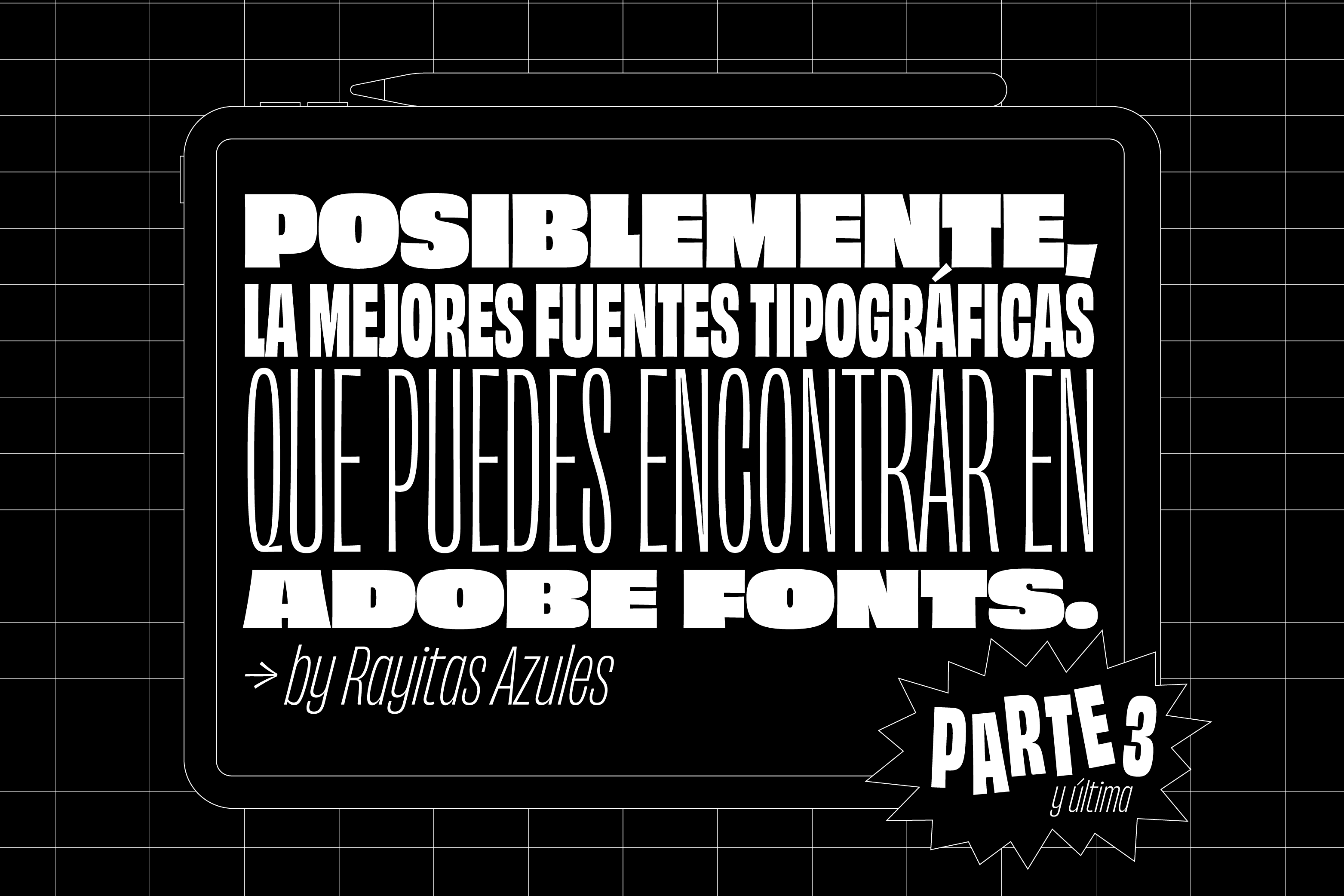
Finalizamos nuestra exploración en busca de las mejores fuentes tipográficas que podemos encontrar en Adobe Fonts. En la primera entrega nos centramos en las serifs y las sans, estas divididas en tres grandes grupos, grotescas, geométricas y humanistas; y la segunda la dedicamos en exclusiva a las display.
En esta tercera y última, vamos a hablar de scripts, monoespaciadas y las que hemos agrupado bajo el epígrafe «trampa de tinta». Quizá no sea en sí mismo un estilo tipográfico; se trata de un recurso técnico, conocido desde los mismos inicios de la imprenta, que con el tiempo ha ido adquiriendo peso estético. Empecemos por aquí.
Trampa de tinta
Las llamadas trampas de tinta surgieron con la finalidad de optimizar la distribución de tinta en las impresiones de tipografías de pequeño tamaño. Consiste en eliminar ciertas áreas de las letras, generalmente en las intersecciones entre las distintas partes de su anatomía, con el fin de evitar una acumulación excesiva de tinta, al expandirse esta de manera natural durante la impresión.
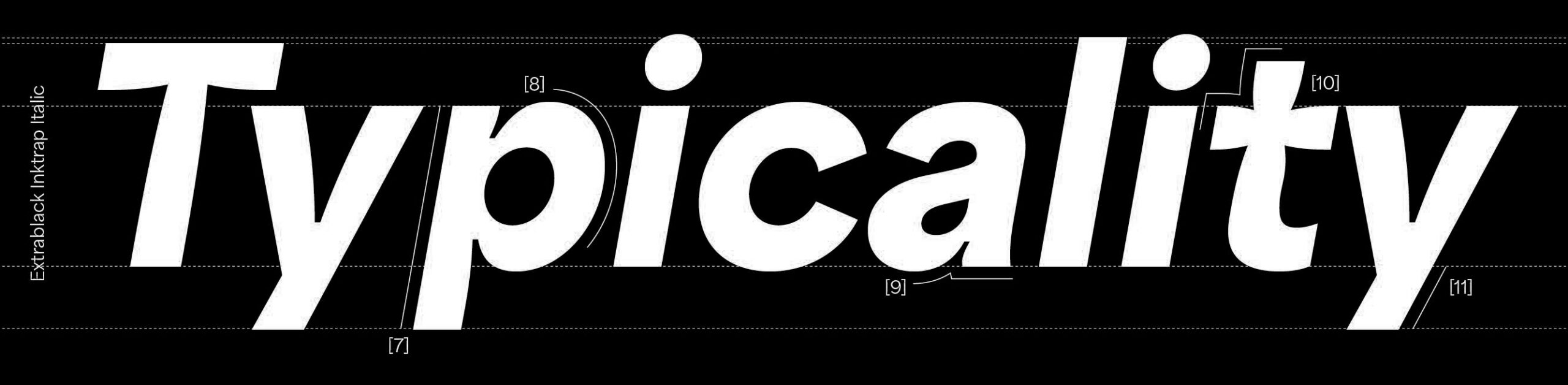
Las trampas de tinta o ink traps pueden ser sutiles o descaradas y erigirse en parte central del ADN de una tipografía. BC Novatica es una grotesca con un cierto toque setentero según sus autores, la fundición checa Briefcase. En ella destacan unas sutiles hendiduras, perfectamente integradas en la arquitectura de la letra, que en tamaños grandes aportan singularidad.
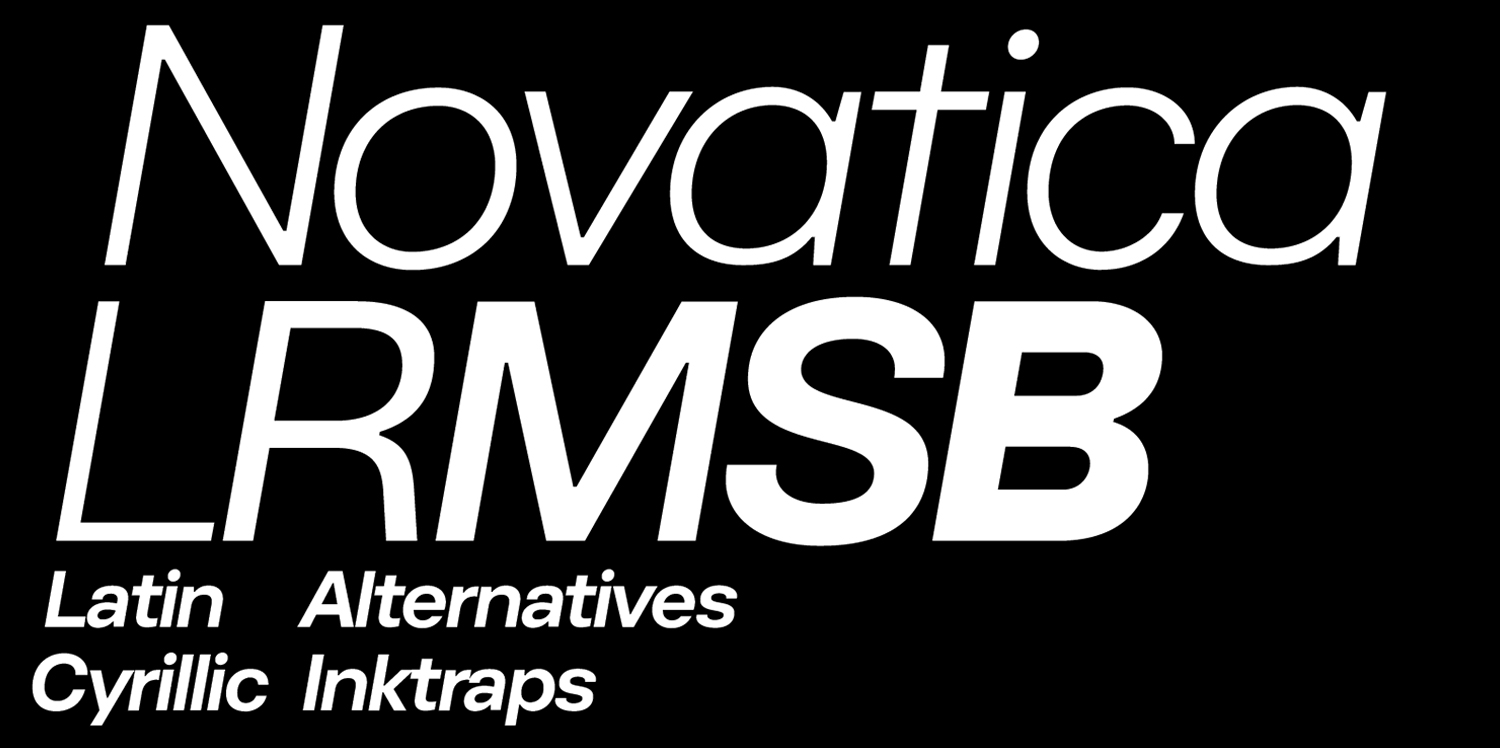
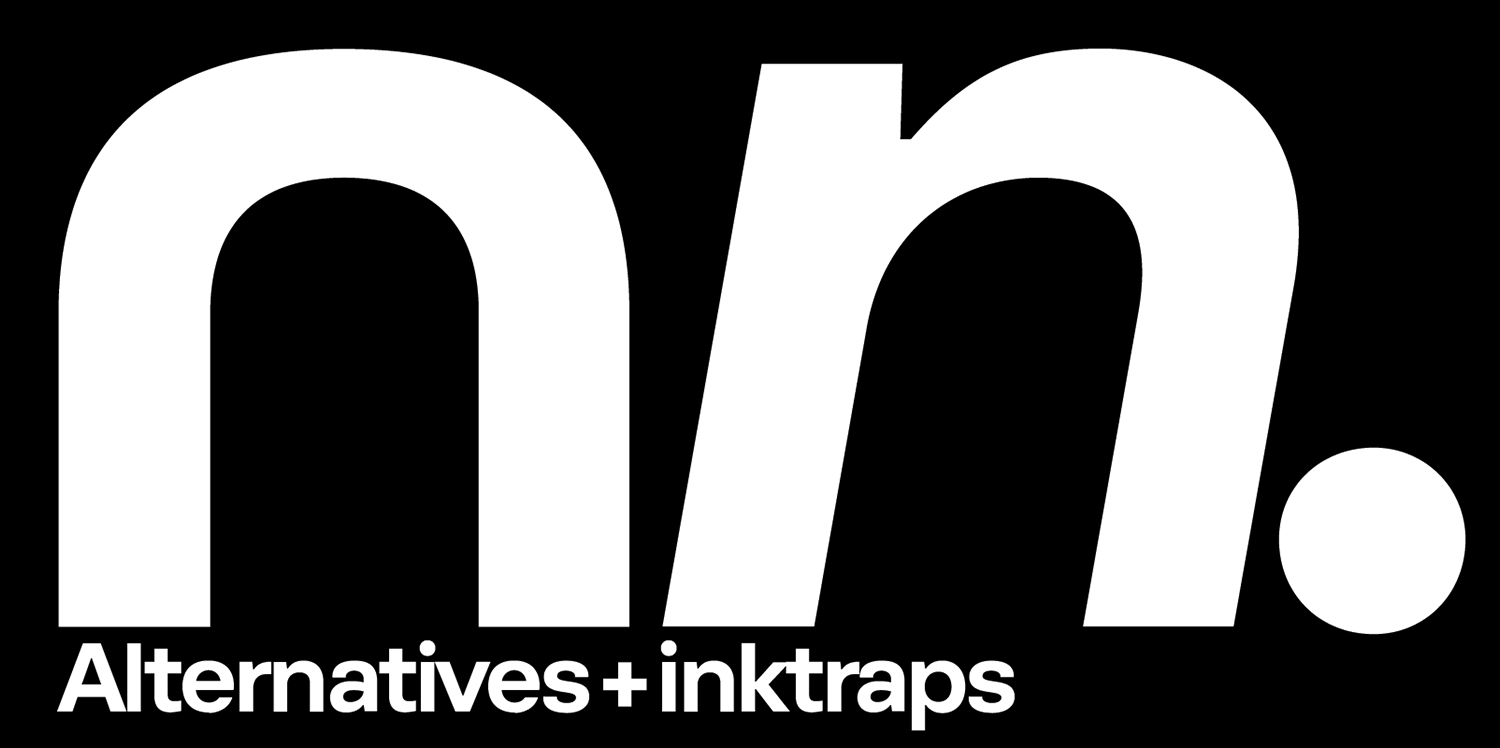
Halyard es una amplia familia tipográfica grotesca diseñada por Darden Studio que en su versión Micro presenta unas pronunciadas trampas de tinta. Ello le otorga un aspecto distintivo, desafiante y excéntrico de lo más atractivo.
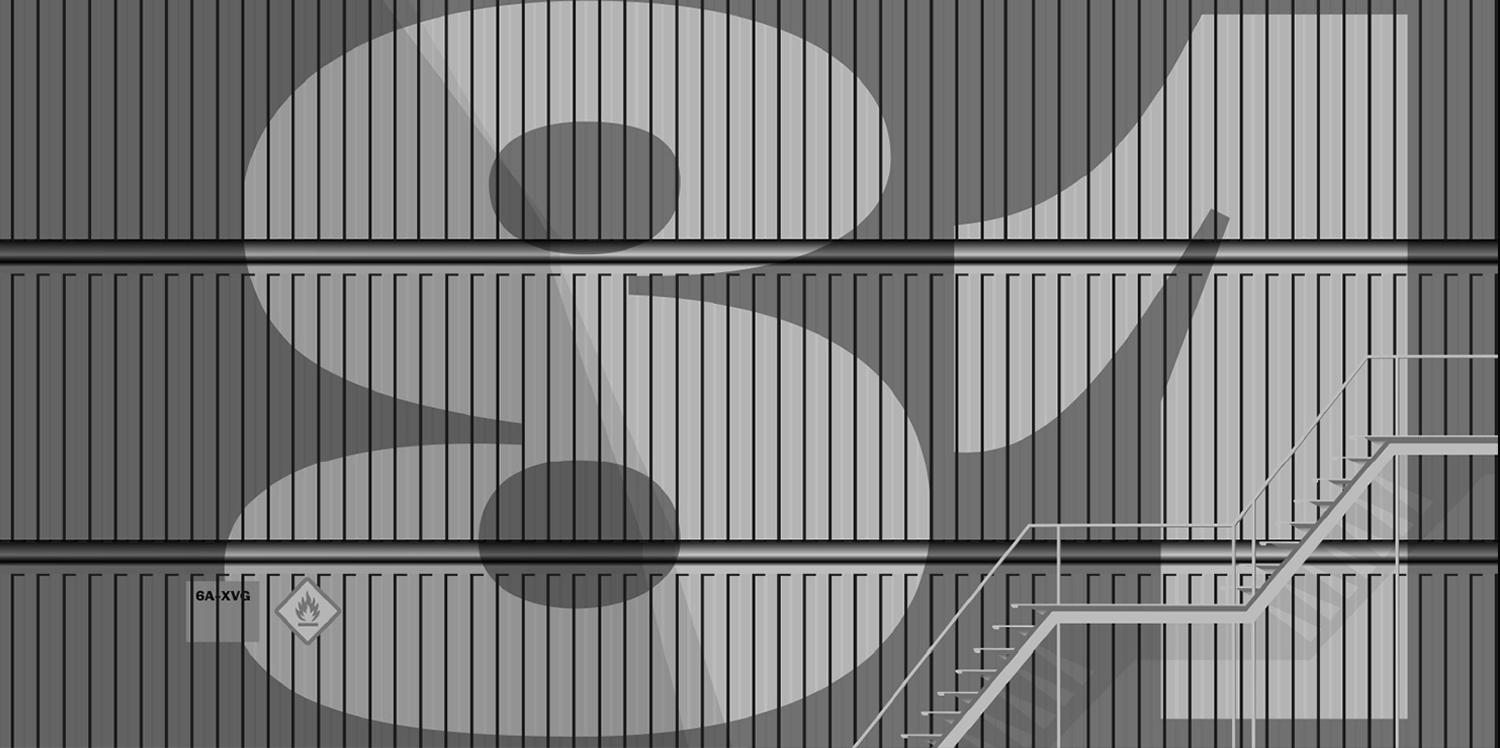
La propuesta de Blaze Type es Area Inktrap, variante de Area, una extensa familia geométrica. Las dos versiones de Area Inktrap, Regular y Extended, fuerzan la estructura de la letra y con ello consiguen una atrayente tensión visual.
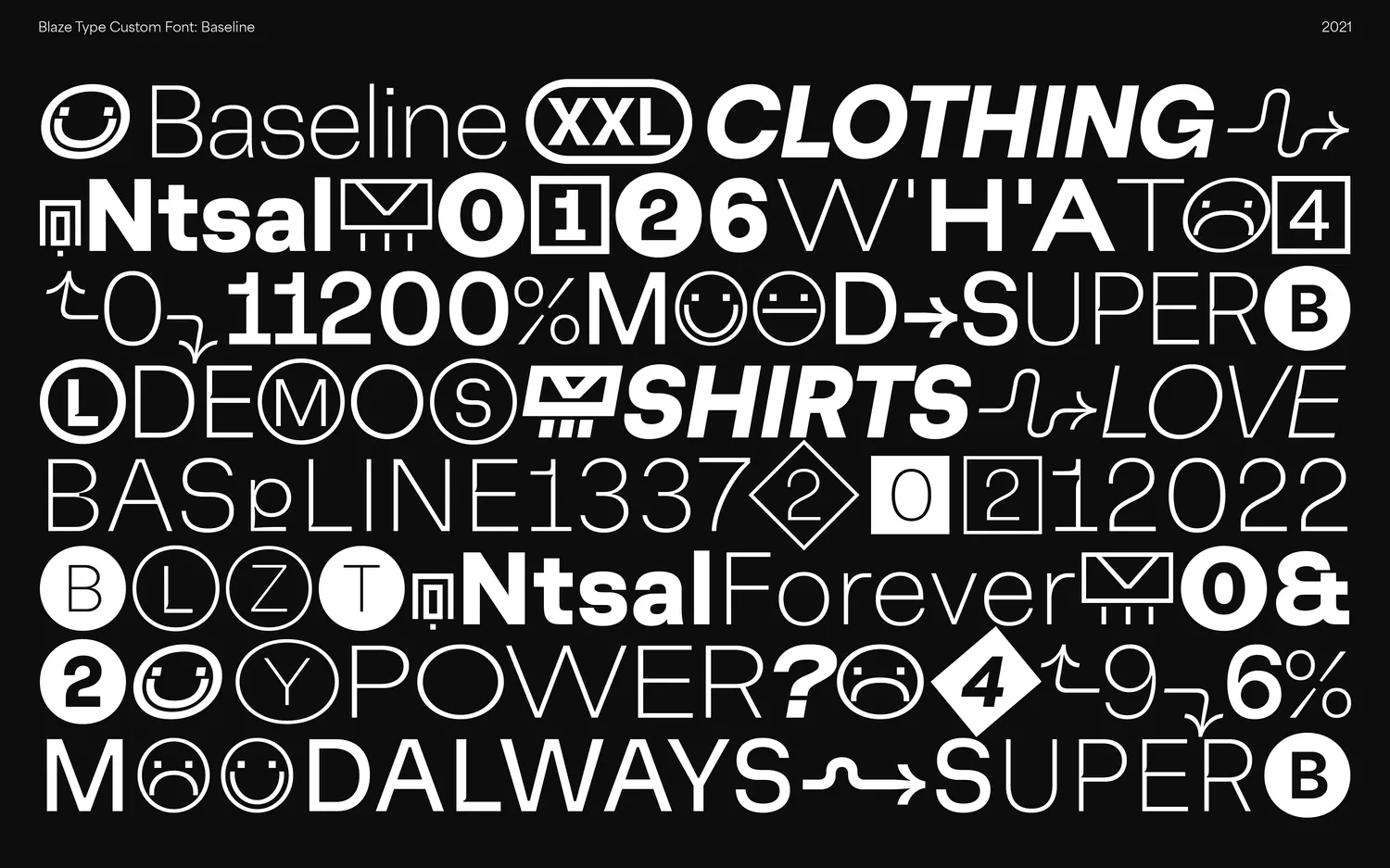
En Brevier, diseñada por Riccardo Olocco para C-A-S-T, el concepto trampa de tinta es el centro de gravedad de una propuesta estética de tintes sci-fi y rotunda personalidad. Pero no nos dejemos llevar por la primera impresión, pues Brevier está concebida para tamaños pequeños —Brevier era el nombre que los antiguos tipógrafos usaba para nombrar a los tipos de ocho puntos— y sus característicos ángulos internos tienen la finalidad de mantener una óptima legibilidad hasta en las condiciones más adversas de impresión. Podemos ver claramente lo que dijimos al principio, cómo la inevitable dispersión de la tinta se ve compensada por estas pequeñas «trampas» colocadas estratégicamente en las intersecciones.
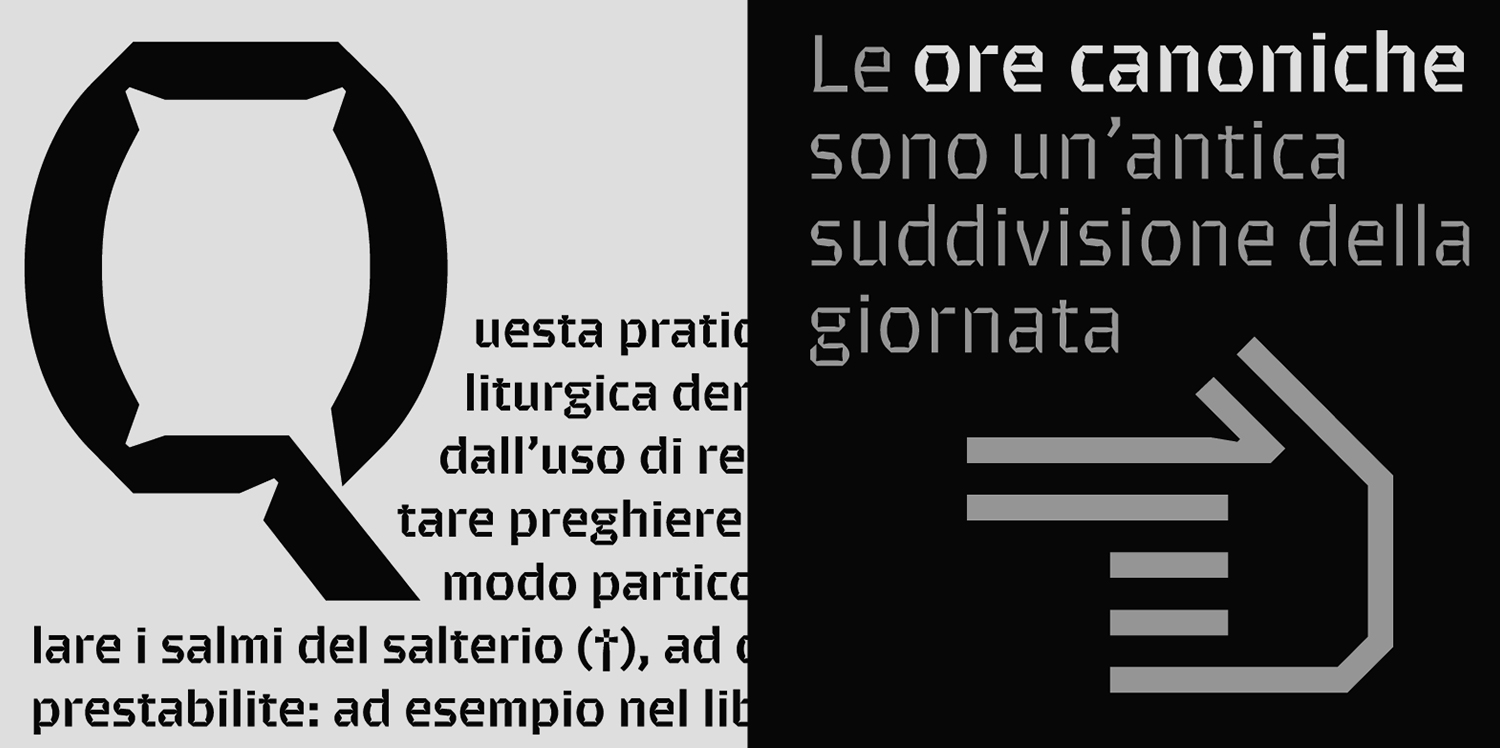
Monoespaciadas
Adoramos las monoespaciadas, lo hemos dicho muchas veces. Y en esta inmersión en lo mejor de Adobe Fonts no podían faltar.
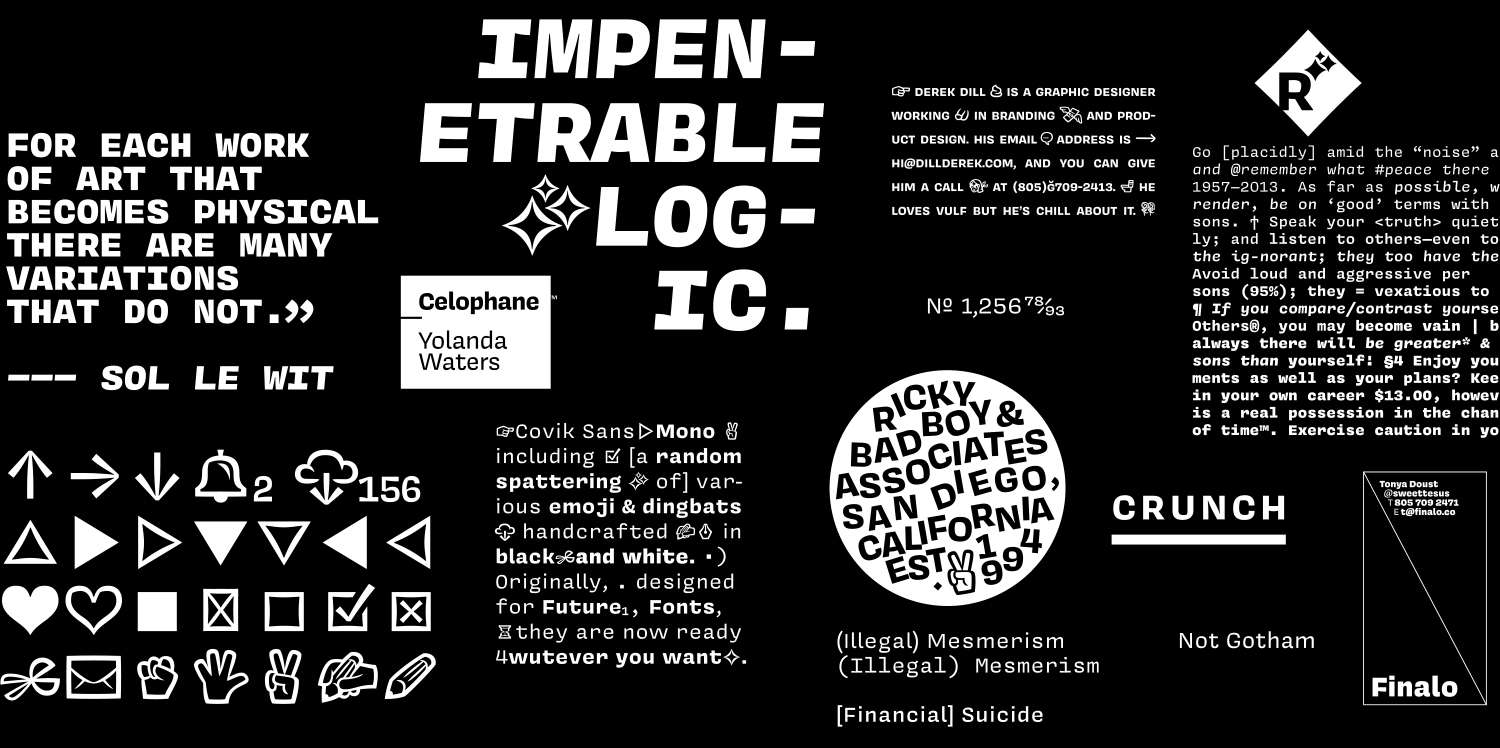
James Edmondson es el singular personaje tras OH no Type, autor de algunas de las tipografías más interesantes de los últimos años. Edmondson, que a pesar de su juventud posee hechuras de sabio bienhumorado, razona que la mayor parte del diseño tipográfico consiste en buscar la manera de encajar el espacio alrededor de una determinada forma de letra, pero en el caso de las monoespaciadas, por contra, de lo que se trata es de encajar la forma de la letra en un espacio determinado. Covik Sans Mono se diseñó para ser la tipografía de Future Fonts y en principio se concibió como una «falsa» mono, es decir, como una mono pero espaciada proporcionalmente, de ahí esa i sin remates, aunque finalmente se acabó incluyendo una versión monoespaciada genuina.
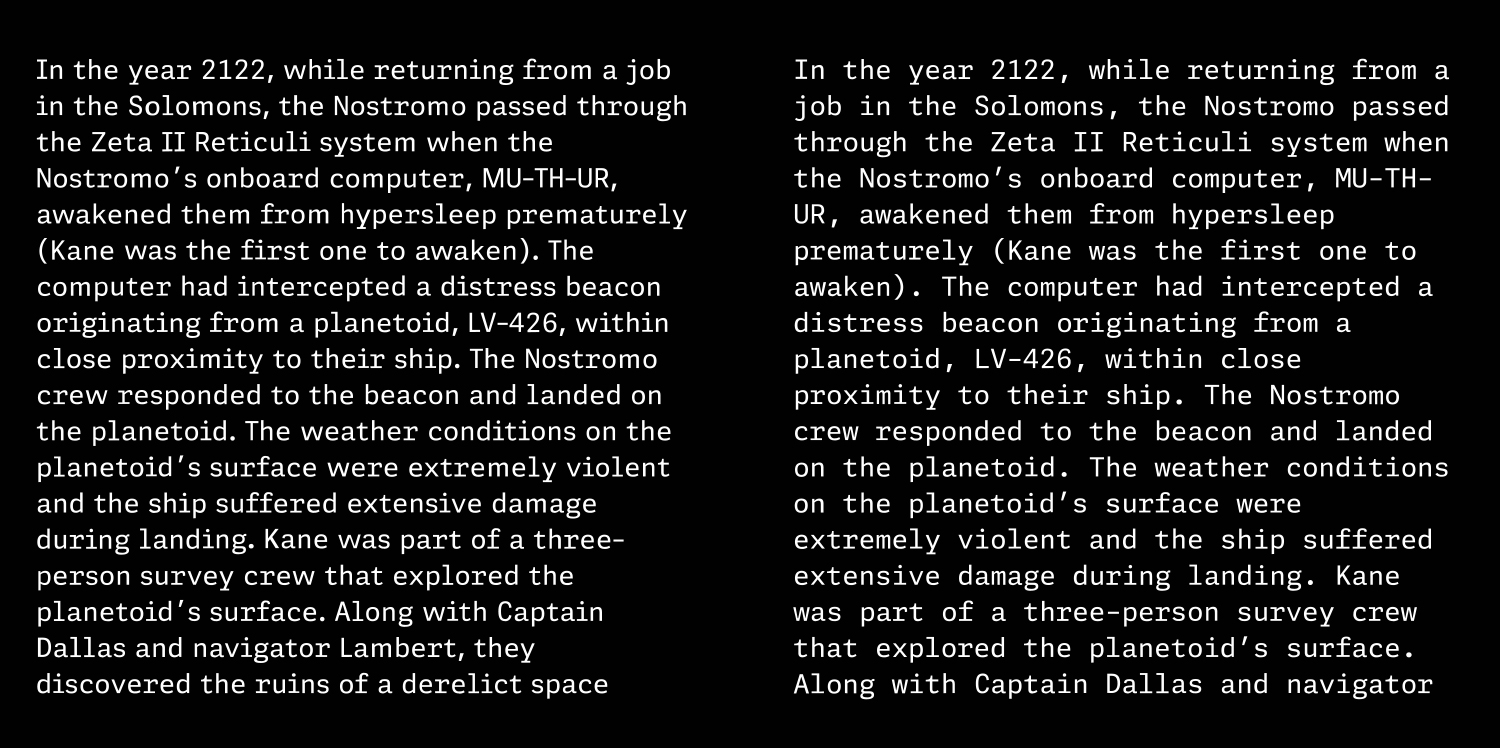
Adelle Mono y Adelle Mono Flex son la visión de TypeTogether sobre las dos naturalezas de las monoespaciadas, una técnica y otra estética. Por un lado, Adelle Mono cumple con la necesidad de mantener la claridad y la eficacia en las extensas líneas de código tanto en estructura como en espaciado y, por otro, Adelle Mono Flex mantiene la estructura pero modula el espaciado con el fin de proporcionar una lectura «normal». Además, existe una versión variable para un espaciado intermedio.
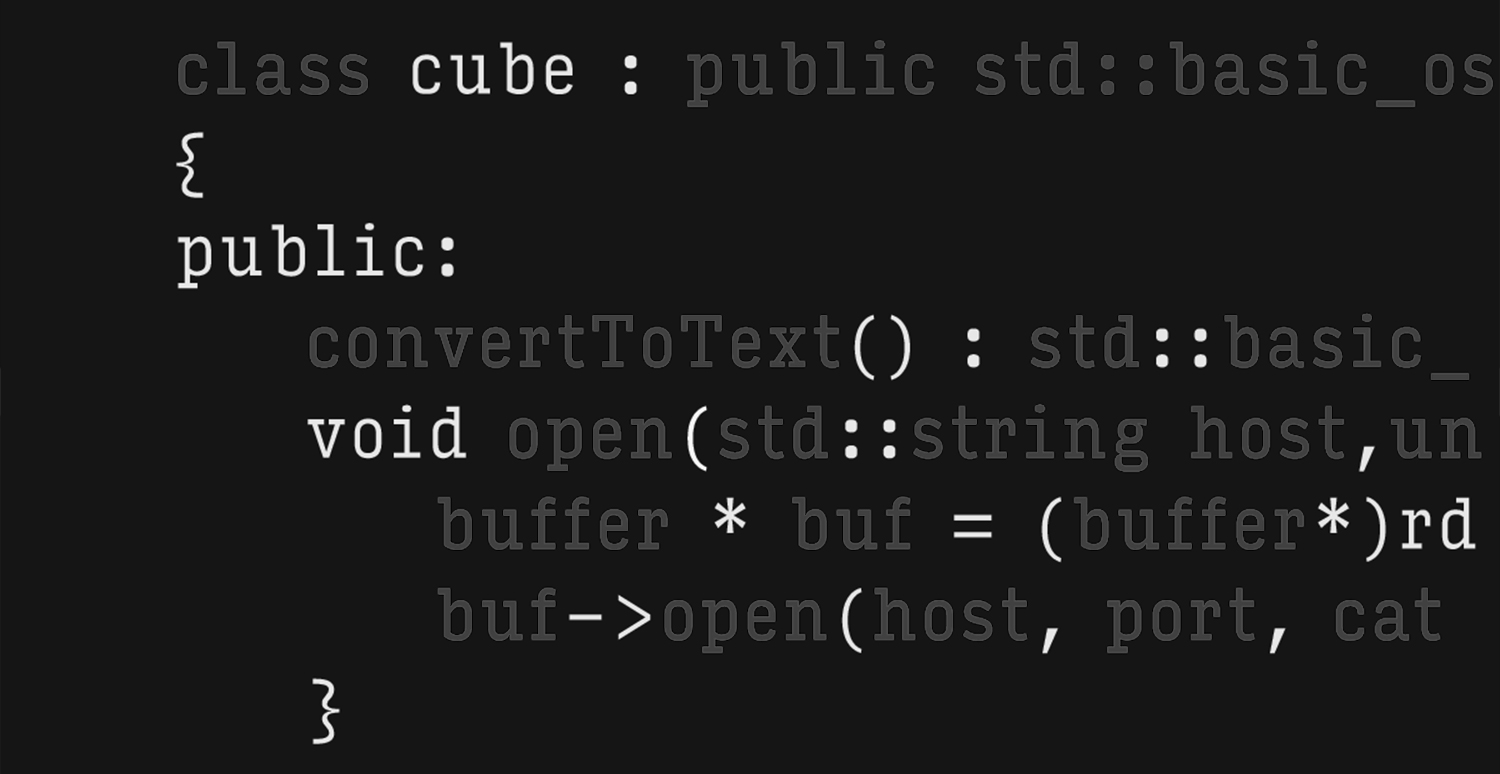
Input Mono es la propuesta del diseñador tipográfico estadounidense David Jonathan Ross para renovar el aspecto estético de la habitual retahíla de datos de programación. Al igual que Adelle Mono, que acabamos de ver, presenta una versión mono canónica —esto es, caracteres fácilmente distinguibles, puntuación de tamaño generoso en comparación con las letras (en código todo cuenta por igual) y espaciado ancho y siempre igual— y una adaptación de espaciado proporcional que conserva el aspecto mono. Además incorpora una versión sans y otra serif, lo que convierte a Input en un fantástico artefacto de diseño.
Finalizamos el repaso a las monoespaciadas con dos referencias más, ambas distribuidas bajo licencia de código abierto. La primera es Anonymous, de Mark Simonson, una mono de una elegante presencia. Y la segunda es Space Mono, propuesta monoespaciada de Google Fonts. Diseñada por Colophon Foundry, Space Mono (el nombre tiene cierta gracia) es una más que interesante exploración de los límites de la tipografía de ancho fijo inspirada en la sci-fi más pop.
Script y caligráficas
Las script son paradójicas por naturaleza, pues la tipografía aspira a desvincularse del gesto manual, mientras que ellas realizan el viaje en dirección contraria: es tipografía que emula o se inspira en la caligrafía. Se trata pues de territorio fronterizo, un camino de ida y vuelta que, como en otras disciplinas artísticas, puede llegar a ser enormemente fructífero.
Acabamos esta serie de tres post dedicados a explorar Adobe Fonts con Confiteria Script, diseñada por Julieta Ulanovsky y Sol Matas para Sudtipos. Se trate de una elegantísima recreación de las inscripciones de crema o chocolate que se realizan en los pasteles en las antiguas y distinguidas confiterías que todavía es posible encontrar en algunas ciudades entre tanta franquicia sin alma. Confiteria Script pretende ser inocente e idealista, lenta como el tiempo en el interior de estos singulares establecimientos.